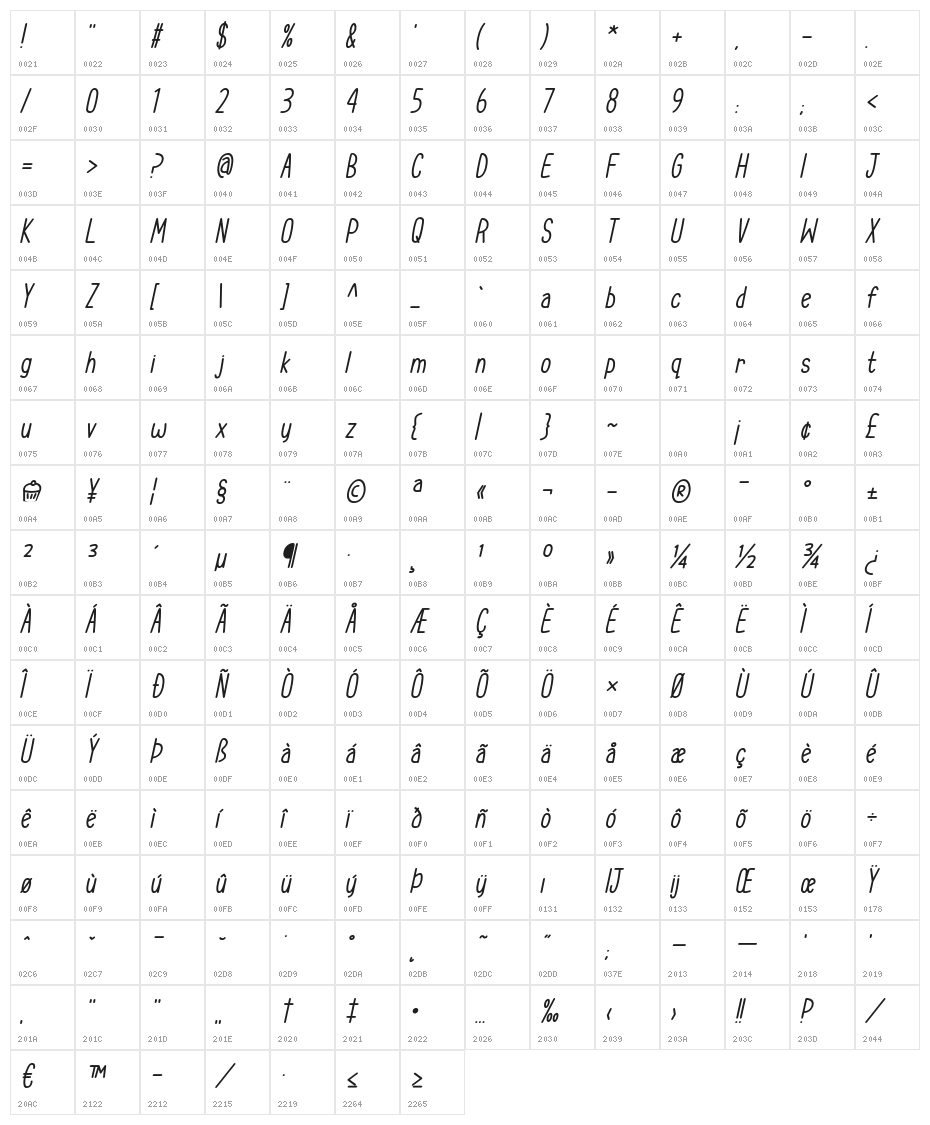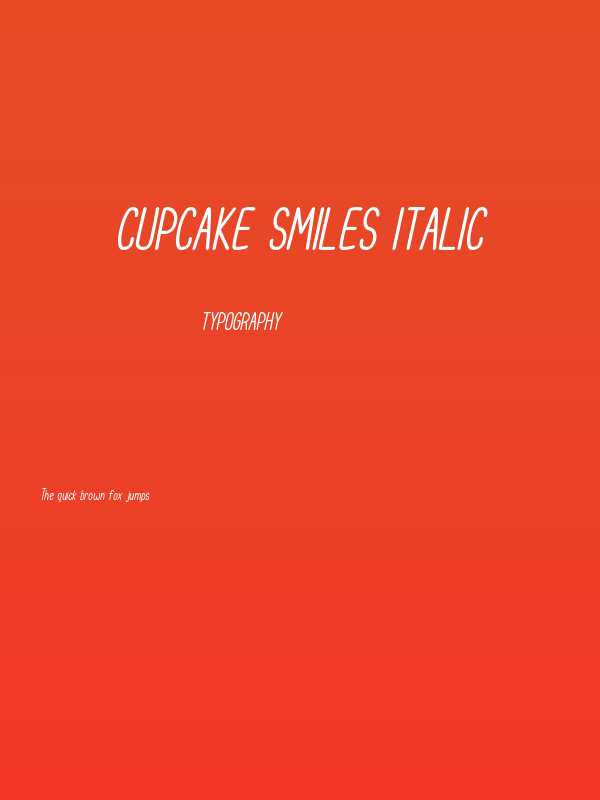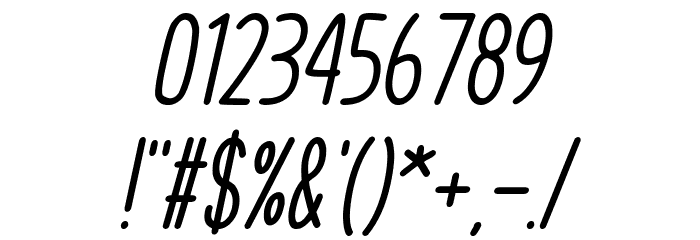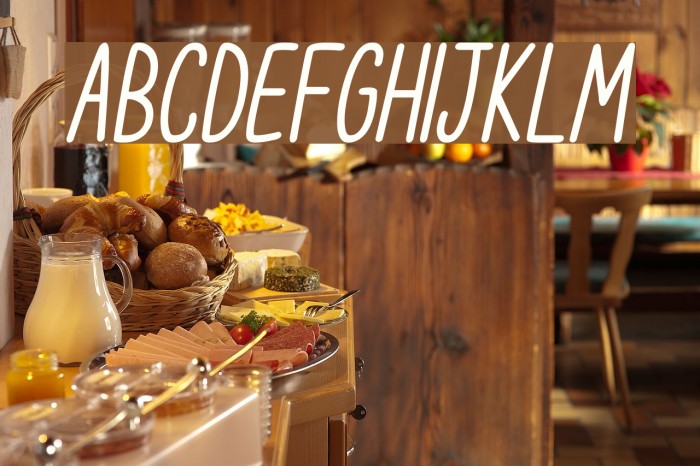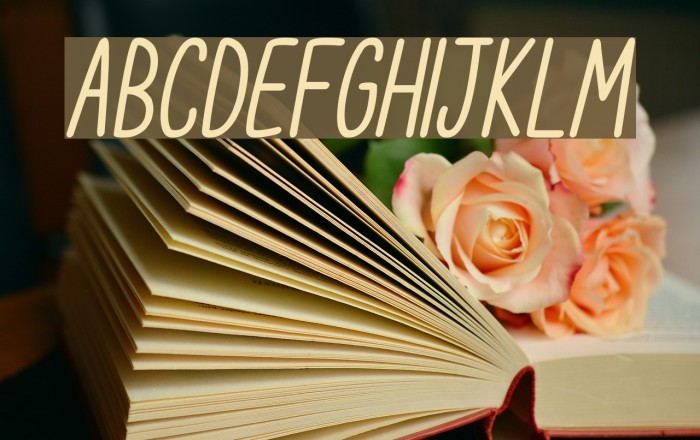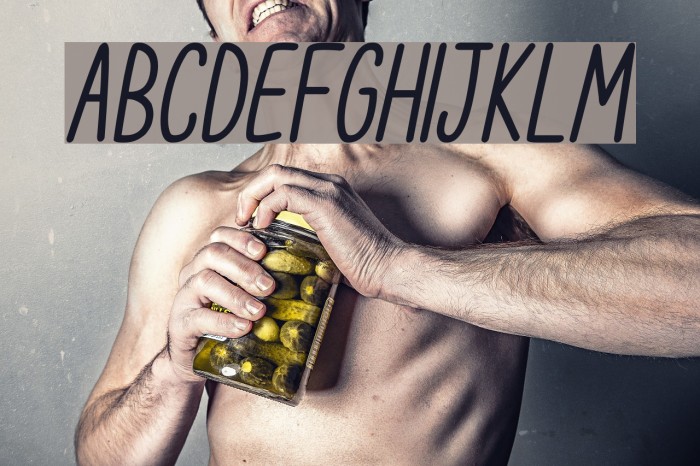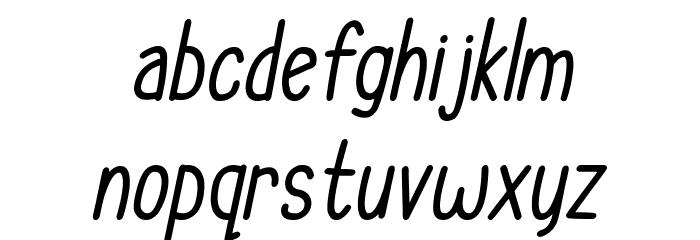
Cupcake Smiles Italic Font
Chequered Ink - chequered.ink/
| Gesamtstil | Casual |
| Anwendungsfall | Headlines, Logos, Informal Text |
| Vorgeschlagene Projekte | Ideal for greeting cards, children's books, playful branding, and social media graphics. |